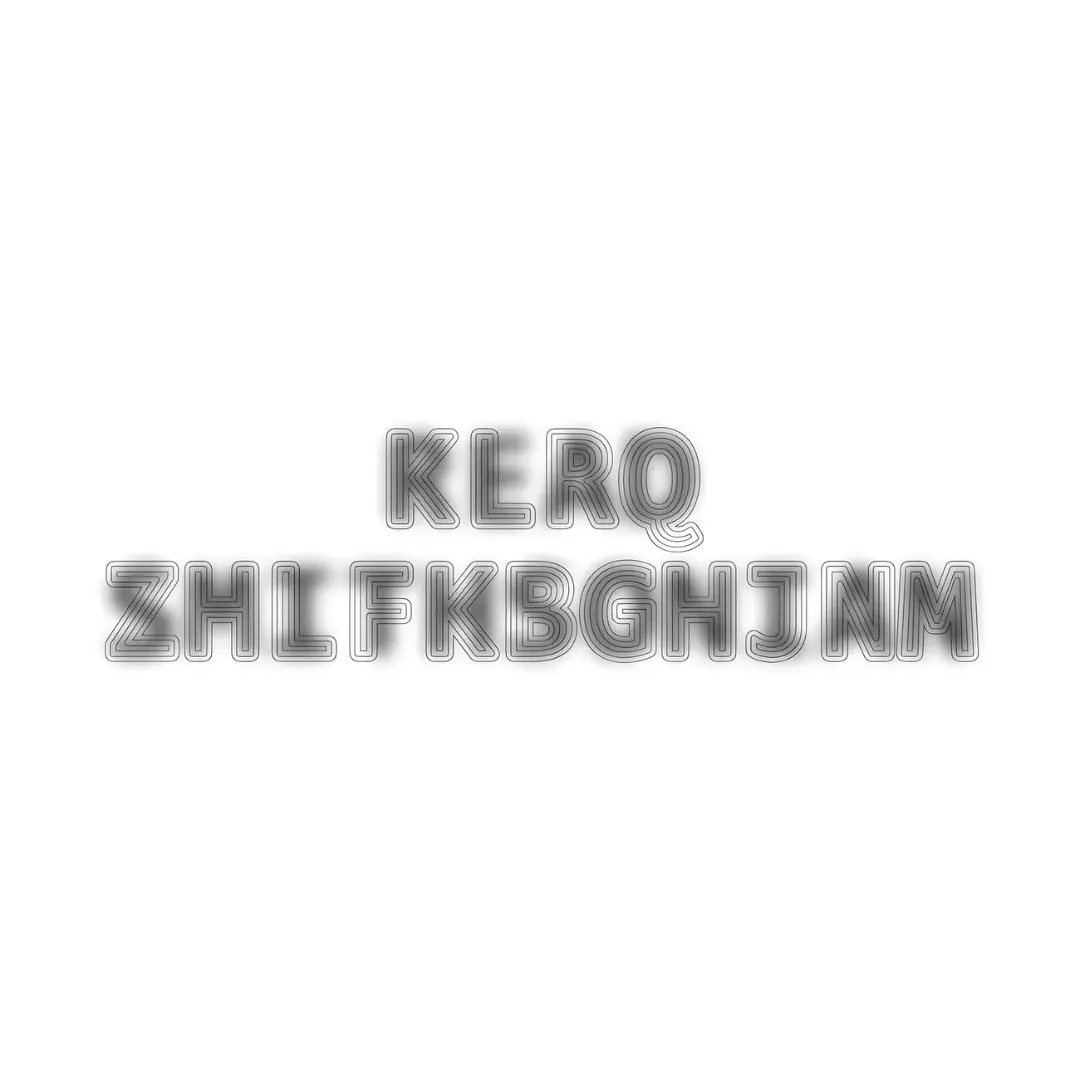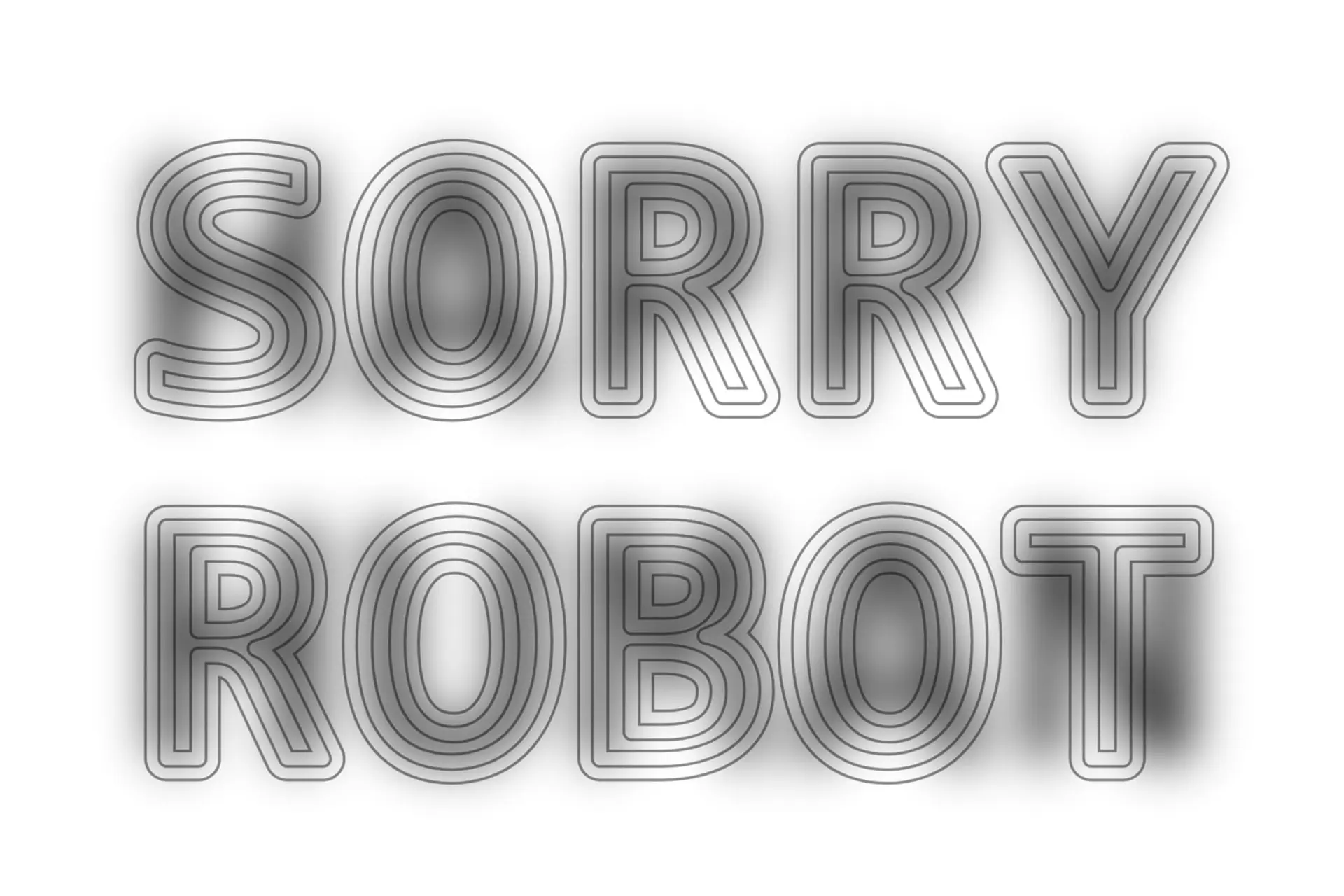
طراحان و دانشمندان کامپیوتر فونتهای جدیدی توسعه دادهاند که برای انسانها خوانا بوده اما رباتهای هوش مصنوعی را به اشتباه میاندازد.
طراحان و دانشمندان علوم کامپیوتر با بهکارگیری خطای دید و تغییر در کدهای ساختاری، تایپفیسهای جدیدی موسوم به Decoy Font خلق کردهاند. هدف اصلی توسعهی ابزارهای نامبرده، جلوگیری از خزش خودکار رباتها و سرقت نوشتههای انسانی توسط مدلهای زبانی بزرگ است.
روش استتار این فونت نسخهای مدرن از خطای دید تصاویر ترکیبی بهشمار میرود؛ روشی که پژوهشگران امآیتی در سال ۲۰۰۷ معرفی کردند. فونت ابداعی از دو لایه متن تشکیل شده که یک لایه با خطوط واضح در جلو و لایهی دیگر بهصورت تار و تیره در پسزمینه قرار دارد تا خوانایی را برای سامانههای خودکار ناممکن سازد.
اریک لو، بنیانگذار استودیوی میکسفونت، میگوید: «یک روز پس از ارسال پیامک به مادرم متوجه شدم که هوش مصنوعی مدام تلاش میکند پیامهای ما را خلاصه کند و در بسیاری از مواقع این کار را اشتباه انجام میدهد. از اینکه این فناوری به گفتوگوی خصوصی ما نفوذ میکرد کلافه شدم و به روشهایی فکر کردم که بتوان بدون خواندهشدن همهچیز با هوش مصنوعی ارتباط برقرار کرد.»
در آزمایشی دیگر، استودیوهای Seneda & Abrucio و PlayType قلمی به نام ShieldFont را عرضه کردند که نیمی از کلمات محتوایی شامل اسمها، افعال و صفتها را در کد منبع با واژههای تصادفی جایگزین میکند. بیش از ۹۰ درصد متنهای نامفهوم خروجی توسط فیلترهای کیفی هوش مصنوعی رد میشوند.
اریک لو میگوید: «این پروژه بهعنوان کاوشی دربارهی تلاقی هوش مصنوعی و تایپوگرافی آغاز شد؛ اما هدف آن افزایش آگاهی دربارهی دسترسی و توانمندیهای روبهرشد هوش مصنوعی نیز بود. واکنشها نشان میدهد افراد زیادی خستگی شدیدی از هوش مصنوعی حس میکنند و خواهان راهی برای دفاع از خود در برابر حضور این فناوری در زندگیشان هستند.»